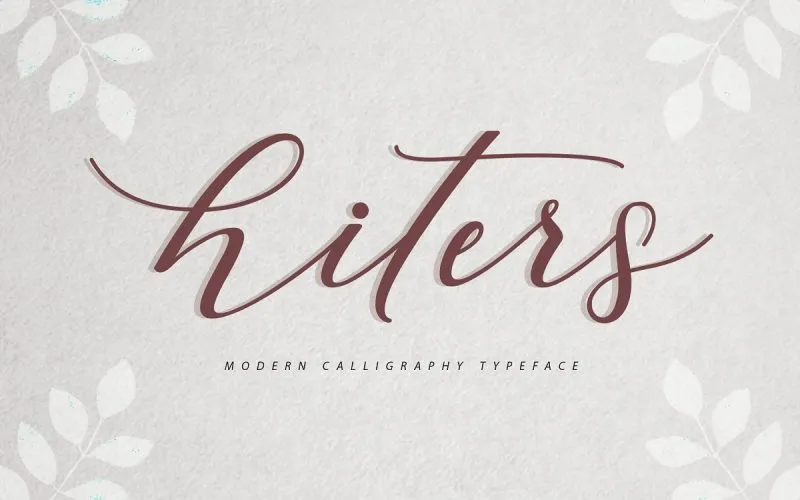
Introduzimos Hiters Font – uma nova tipografia moderna feita em estilo caligrafia. Inspirado no projeto Musafir LAB, esta fonte foi pensada para oferecer um visual encantador e sofisticado a qualquer texto. Hiters Script está equipada com cada letra cuidadosamente moldada, criando uma conexão prolongada que torna seu texto ainda mais bonito. Com seu estilo moderno de caligrafia, esta fonte é perfeita para uma variedade de projetos, como casamentos, convites, cartões de boas-vindas, outdoors, cartões de negócios, citações, cabeçalhos de blog, marca, logotipos, moda e roupas. Tudo isso ajuda a tornar qualquer trabalho mais profissional e charmoso. Com sua elegância única, Hiters Font é uma opção ideal para quem busca deixar seu trabalho ainda mais impressionante e único em todos os momentos que escreve ou desenha com ela. Que tal experimentar adicionar um toque de sofisticação a seus projetos? Hiters Script pode ser o ponto final perfeito que você está procurando!